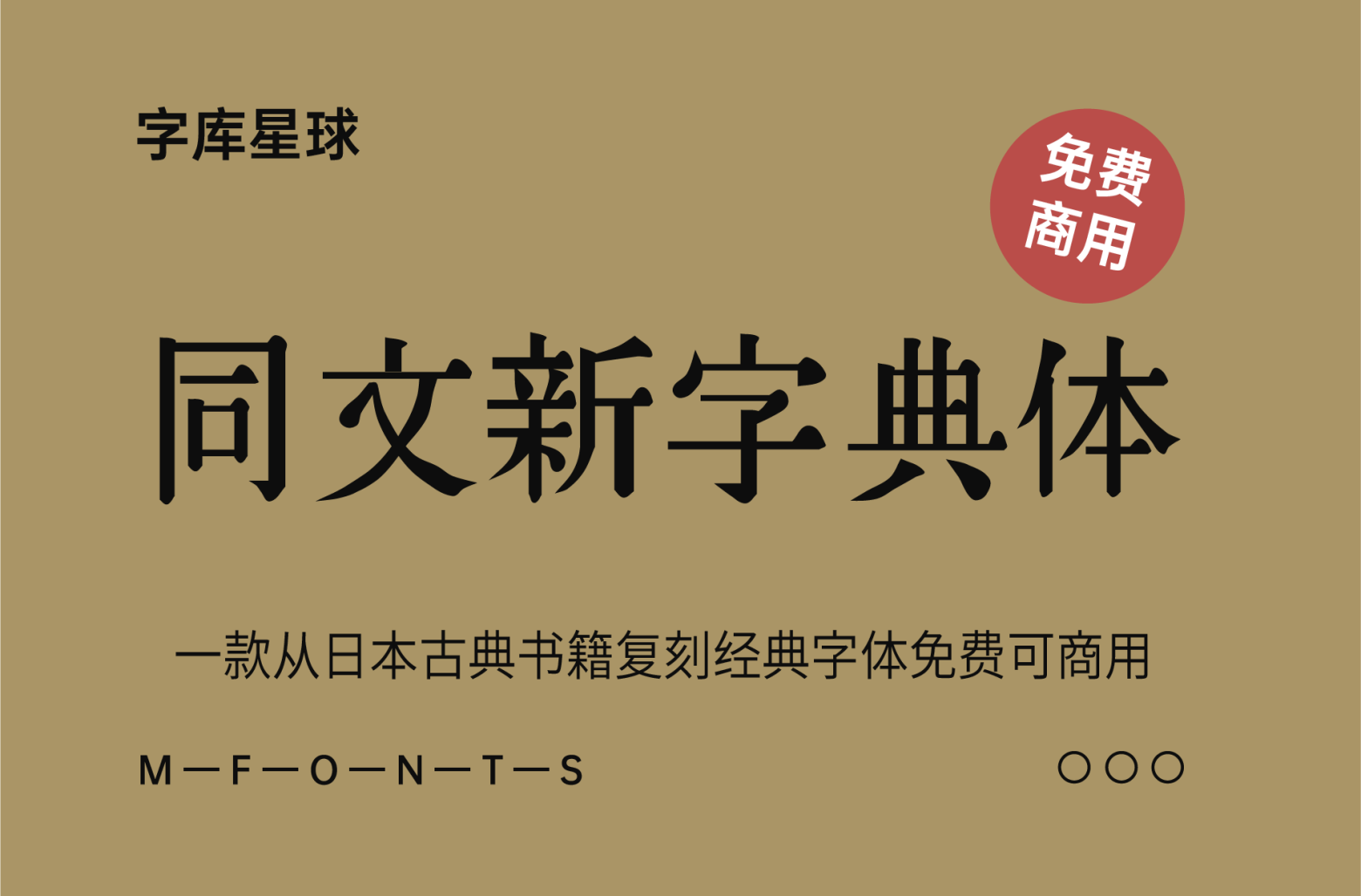
同文新字典体
同文新字典体(出島明朝フォント dejima-tsu3)的作者是日本的Yoshiki Hayashi,他在Github上建立了这款字体的开源项目,同文新字典体是从日本古籍《同文新字典》和《 [東京築地活版製造所]活版見本 》复刻而成的一款字体。
对于古典的复刻字体,之前推荐过黄令东大神制作的《黄令东齐伋体》十分受到大家的喜爱及欢迎,现在的这款字体也是古籍字体复刻。不过猫啃网并没有找到更多的关于《同文新字典》的资料,这是日本明治年间的编著。
因为同文新字典体是一款从古籍复刻而来的字体,所以该字体主要以繁体字为主,也包括部分简体字。